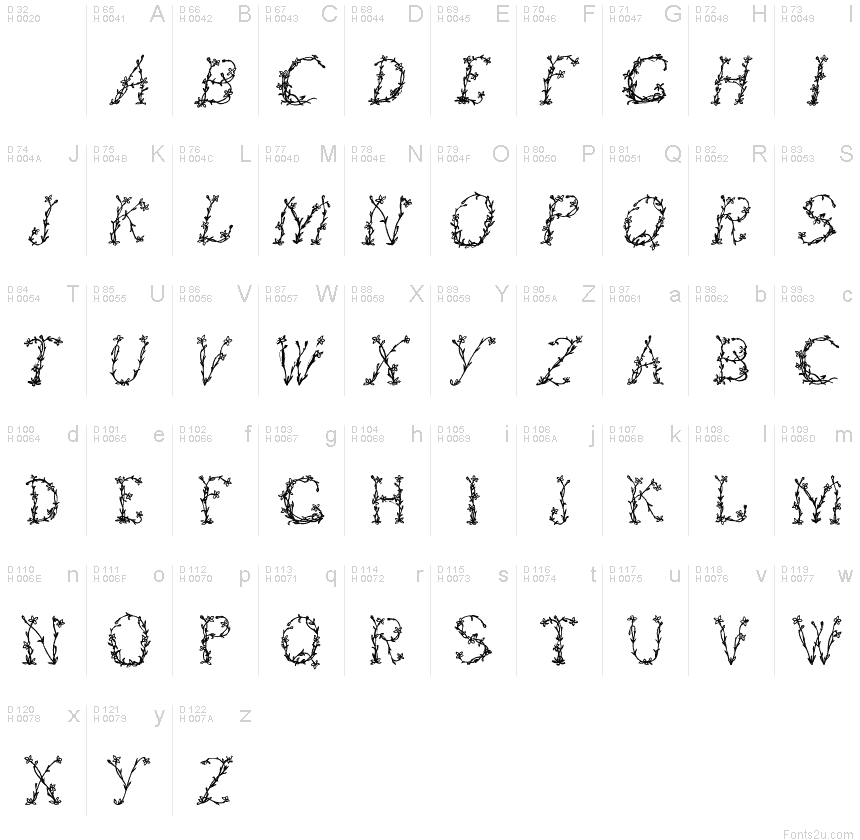
Floral One di M. Klein è un carattere decorativo gratuito che trasforma ogni lettera in un intreccio di viticci disegnati a mano e minuscoli fiori. I tratti ricordano ramoscelli inchiostrati — leggermente irregolari, ricchi di anelli e curve — tanto che il testo sembra cresciuto sulla pagina piuttosto che digitato. Si percepisce un'energia leggera e fantasiosa che suggerisce l'aria di primavera, giardini selvaggi e insegne artigianali affisse su pali di legno.
Questo font gratuito risplende su partecipazioni di nozze, volantini per feste in giardino, packaging eco-friendly, branding per mercati contadini, copertine di libri e grafiche stagionali per i social. Dato che Floral One è ricca di dettagli, lasciatela respirare in dimensioni maggiori e abbinatela a un carattere sans serif pulito per il corpo del testo, così che le forme fogliate restino leggibili e distintive.